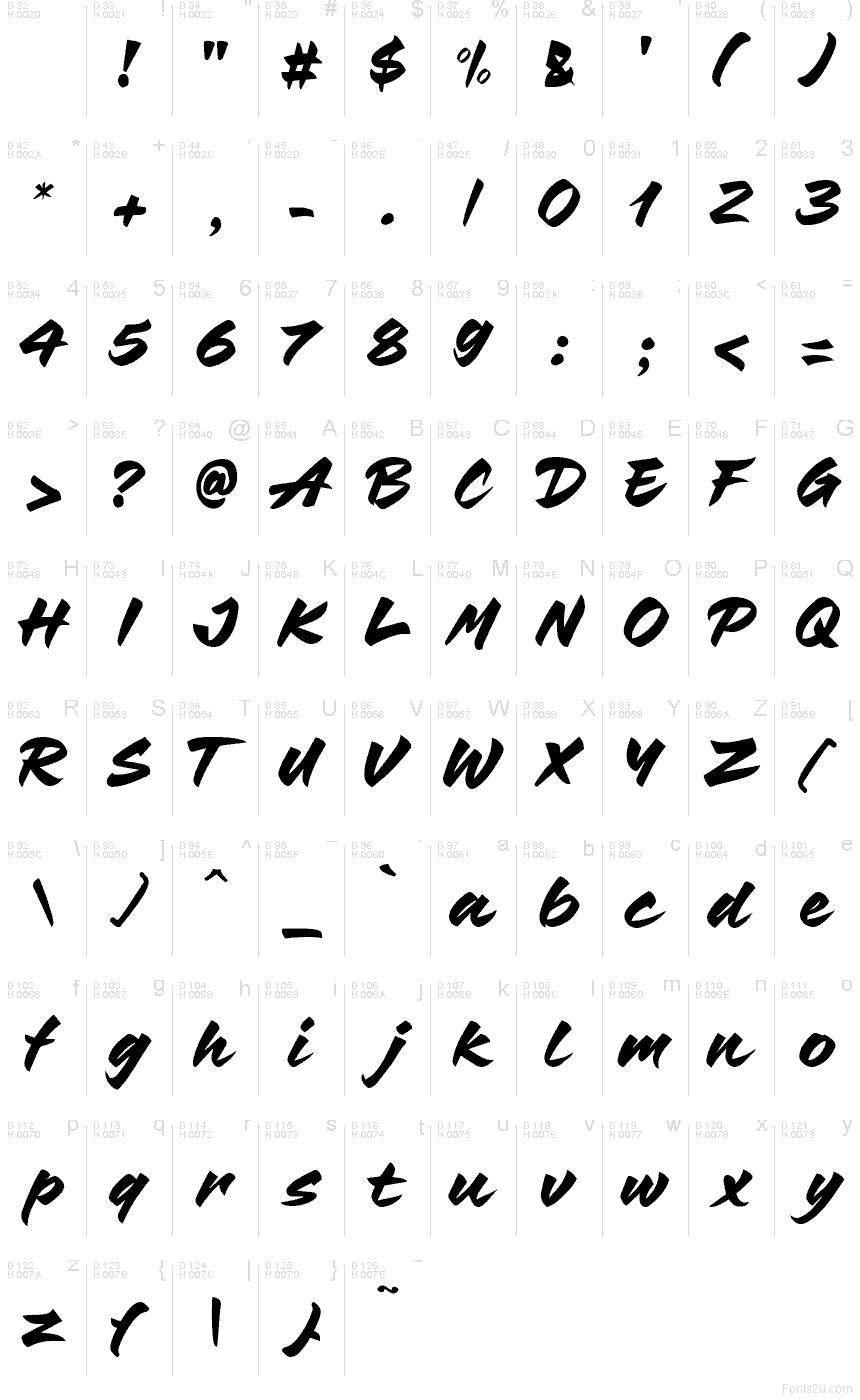
Barbecue Chicken
Barbecue Chicken от BlackFridayFont — это бесплатный шрифт в стиле кистевой каллиграфии с динамикой, характерной для надписей от руки. Буквы отличаются жирными, сочными штрихами, острыми врезками и округлыми петлями, что придает шрифту непринужденный, смелый и слегка грубоватый вид — именно то, что нужно для атмосферы вывесок или уличных граффити.
Он идеально впишется в айдентику фудтраков, этикетки соусов для барбекю, заголовки плакатов, графику для соцсетей и мерч, где бесплатный шрифт должен быть заметным и «живым», а не выверенным. Поскольку штрихи выглядят так, будто были нарисованы одним движением, шрифт также отлично подходит для коротких подзаголовков, титров и логотипов, которым не хватает этой быстрой, «ручной» подачи.